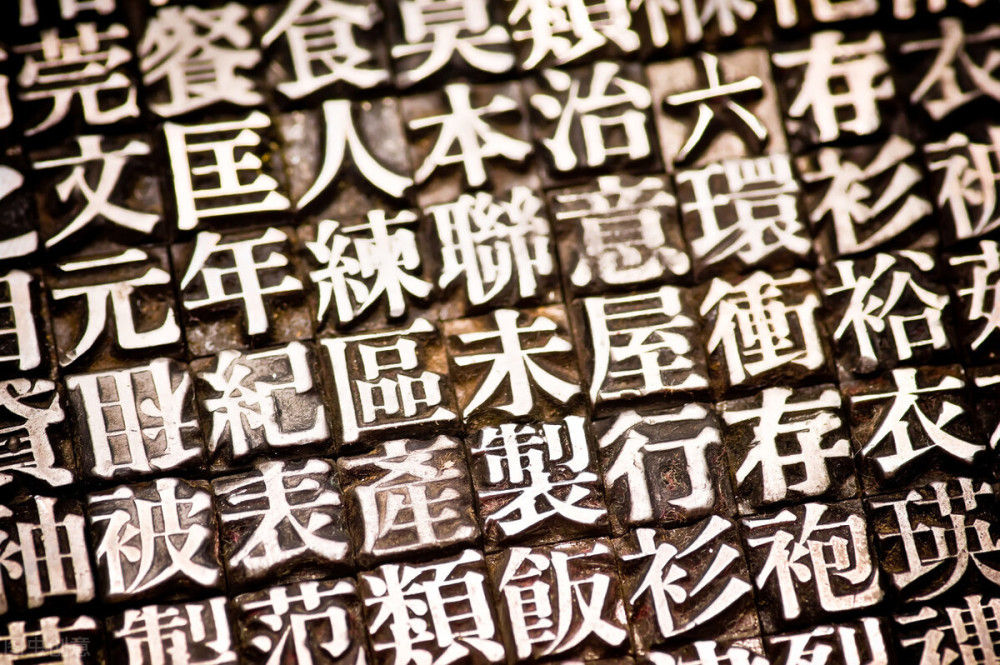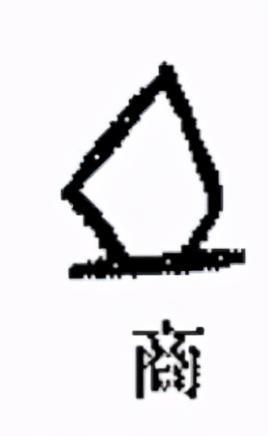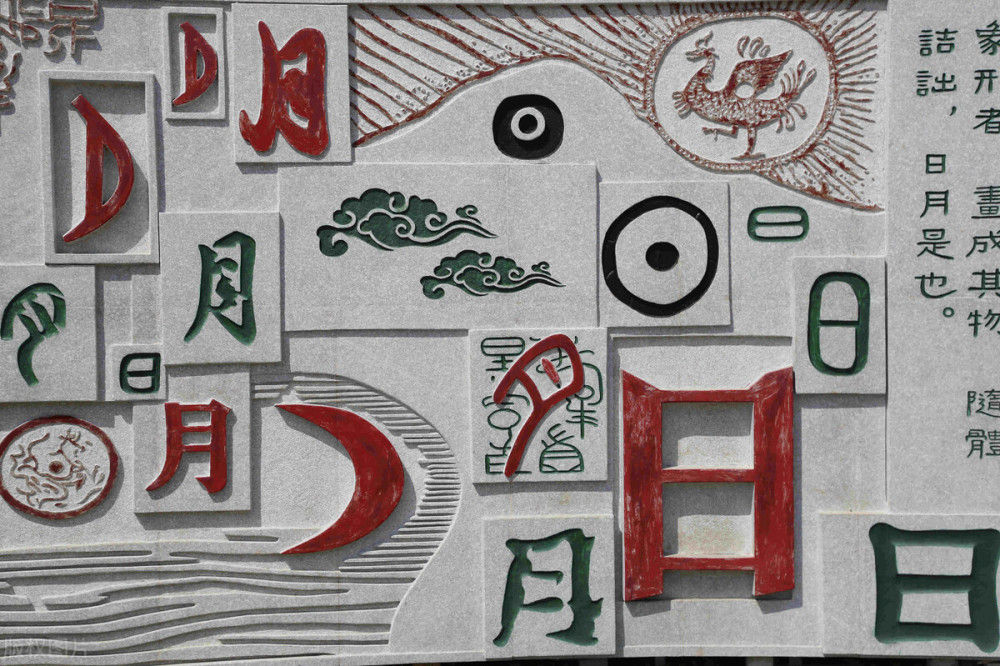
数千年来,自文字产生,他就发挥着重要的作用,我国现今使用的文字都是汉字,从艺术的角度来观察汉字,汉字属于象形文字,其本身不仅具有文字的特性,还是一件完美的艺术品。大家都应该听过这样一句话,汉字中每一个字就是一幅画,就拿社这个字来说吧,看着这个字像什么,像火堆,像土堆,其实他就是土,因为在甲骨文中并没有“社”这个字,而土就代表着社这个字,所以咱们看到了这个样子。
这些字的产生就是根据当时人们的活动产生的,由此可以看出,当时的人有多么注重这些活动。这也从侧面表现了当时人们的一个生活场景。
而我们现在所说的字体设计来源于文字,是根据文字的发展而发展的。实际上,汉字的产生在一定意义上也属于字体设计的诞生,它属于字体设计的一种表现方式,展现了中华文明的丰富内涵。文字在诞生之初,作为传达信息的一种方式,它本身和人类的文明、生活就有着千丝万缕,又相互影响的紧密联系,并且,在岁月的沉淀下,一直顽强的适应社会的发展。从根本上讲,设计的意义也在于流传和适应。
那咱们进行一个字体设计的根本原因是什么呢?
直观的传达平面设计的理念和内容
平面设计的意义就在于将平面设计承载的内容传达给观众。文字的直观表达可以让观众直接了解设计师创作这幅作品的目的,以及理解平面设计的理念。和其他设计方式相比,平面设计采用字体设计的方式更为方便、简洁和直观。
使画面整体美观
一张图里面,除了文字这个要素外,还有其他的要素,将这些要素结合在一起,才能形成一幅设计作品。将字体设计采用合理。主次分明的布局到平面设计中,让字体设计和平面设计其他要素协调合作,让设计师的作品,看起来更加美观,更加具有整体性,满足了受众者的审美需要,得到了精神上的享受和满足。
丰富了作品的内涵
现实生活中,需要平面设计的范围和领域非常广泛。正因为社会的发展,人们物质生活得到满足,开始不断的追逐精神上的满足,尤其是文化素质水平的普遍提高,审美也出现了变化和发展,作为平面设计中一个重要组成部分,字体设计的出现是必然的,字体设计的应用为平面设计增添了活力,改变了以往平面设计的理念。
咱们懂了这些之后,那咱们到底怎么来做呢,其实在字体设计有一样是很重要的,那就是重心,何为重心呢?
重心
物理学上的重心是无论物体怎样放置,其重力总是通过物体内的一个确定点一平行力系的中心,这个确定的点称为物体的重心,而在我们字体设计中的重心就是那个字之间他们对齐的地方。
也就是说他们笔画对齐的地方,不管是有一笔还是几笔,只要的对齐的地方,就是这个字的重心。大家可以看一下自己的字库,还是他们设计的字体,必定是由一笔是对齐的,甭管这个字的位置在哪里。这也就是咱们字体设计里面最重要的地方。
最后,咱们进行字体设计时就可以依照原来的字体进行一个设计,当然你也可以自己设计,但这就要注意我上面说到的重心这个问题了。当然了,最主要的是大家可以去试着做一下,你行动一下,感受一下那个变化,可能你就会有更多的感悟。
而我们最主要的不要忘记我们传承,那是根植在我们骨子里面的东西,即使我们的外观、衣着、相貌发生再大的改变,我也希望我们不要忘记我们的根。